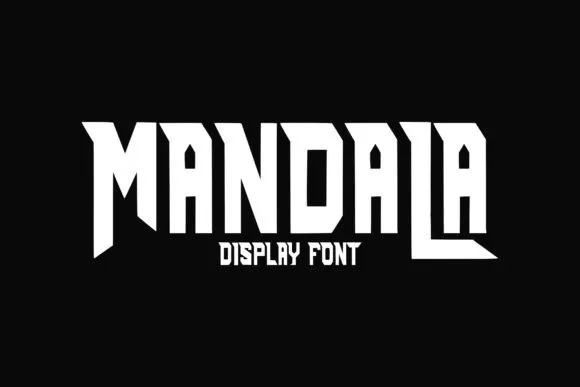
A Mandala é uma elegante escolha para designers que valorizam a mistura única entre clássico e moderno. Este font Display oferece uma combinação sofisticada e ousada, perfeito para trabalhos de logotipos, rótulos, badges, capas de livros, camisetas e embalagens. Desenvolvida pela Arendxstudio e compartilhada no site 99designs, a Mandala traz opção de alternativas estilísticas, conjuntos estilísticos e ligaturas para qualquer aplicação visual criativa. Seja um design de logotipo sofisticado ou uma camiseta inspiradora, a Mandala está aqui para dar vida à sua ideia. Engrena-se em seu próximo projeto com essa font versátil que combina os melhores traços do passado moderno.